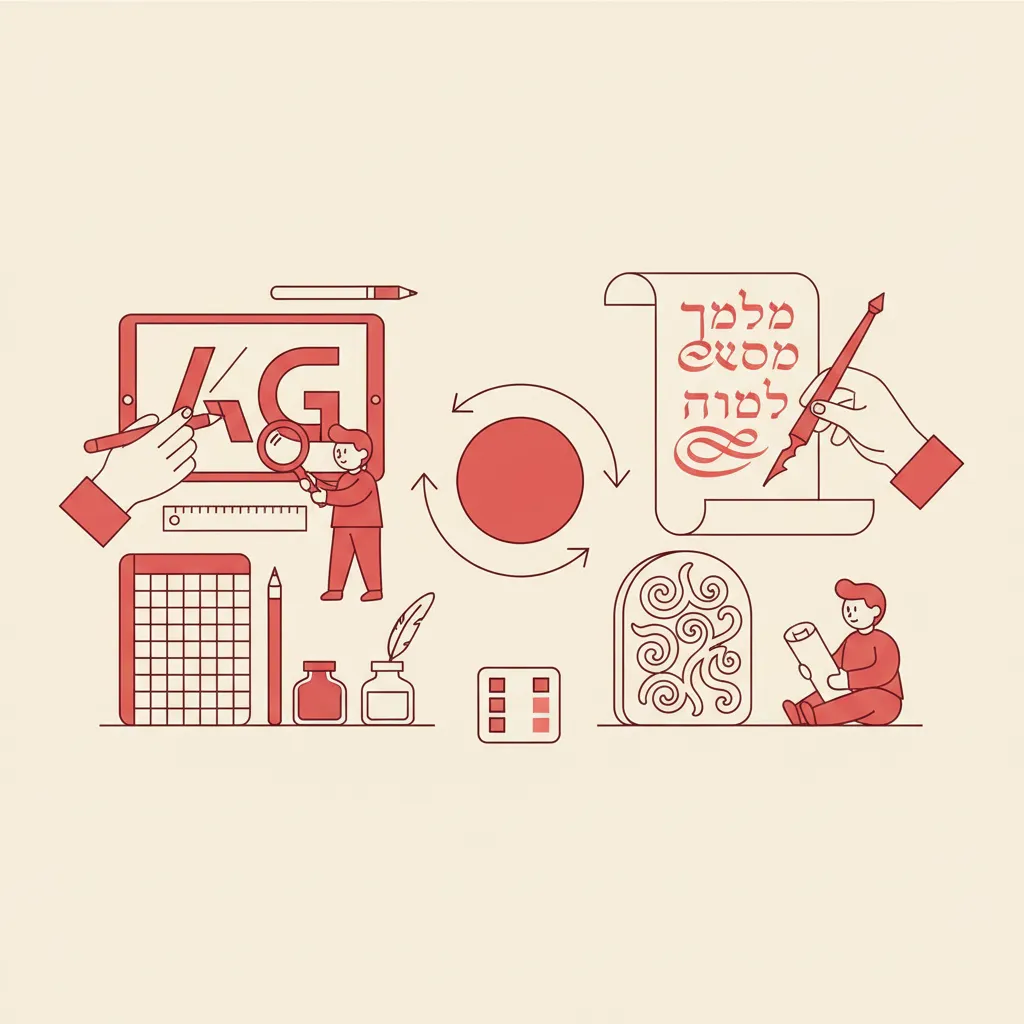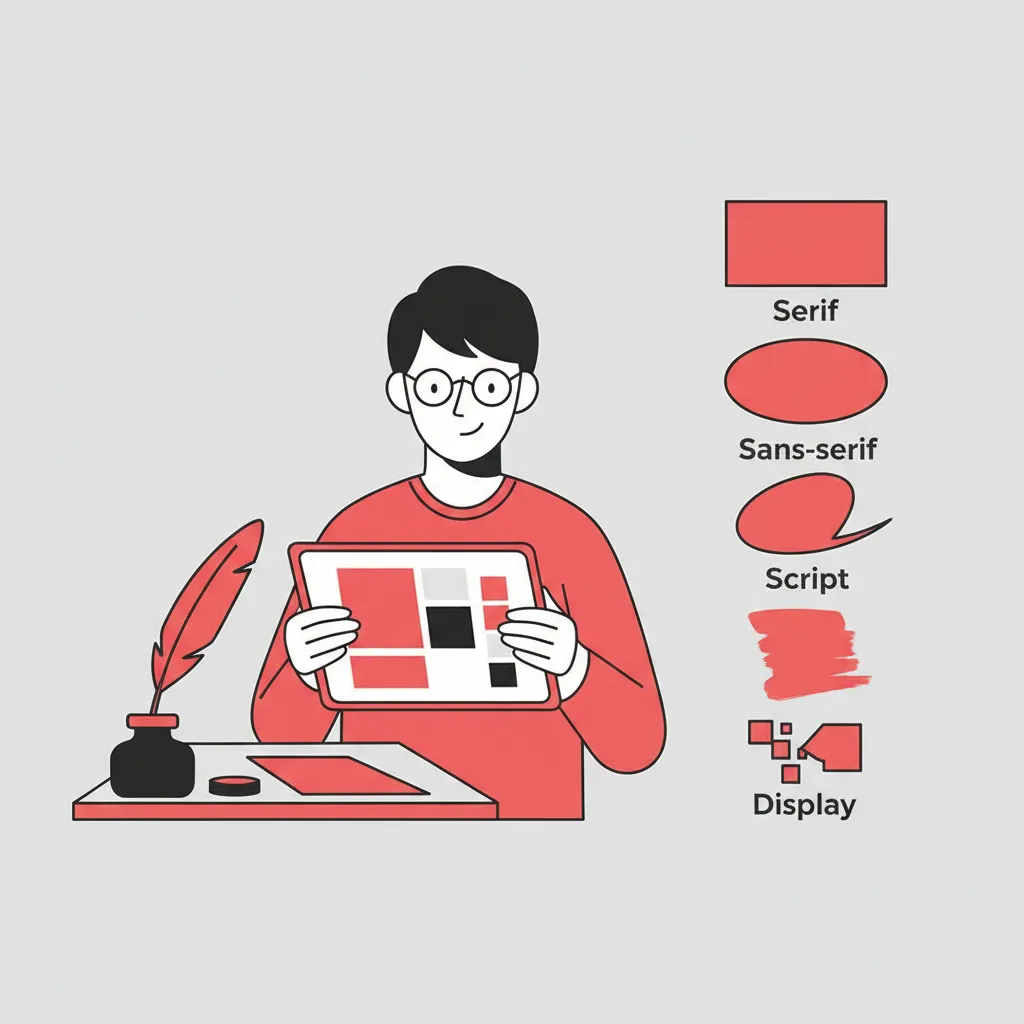
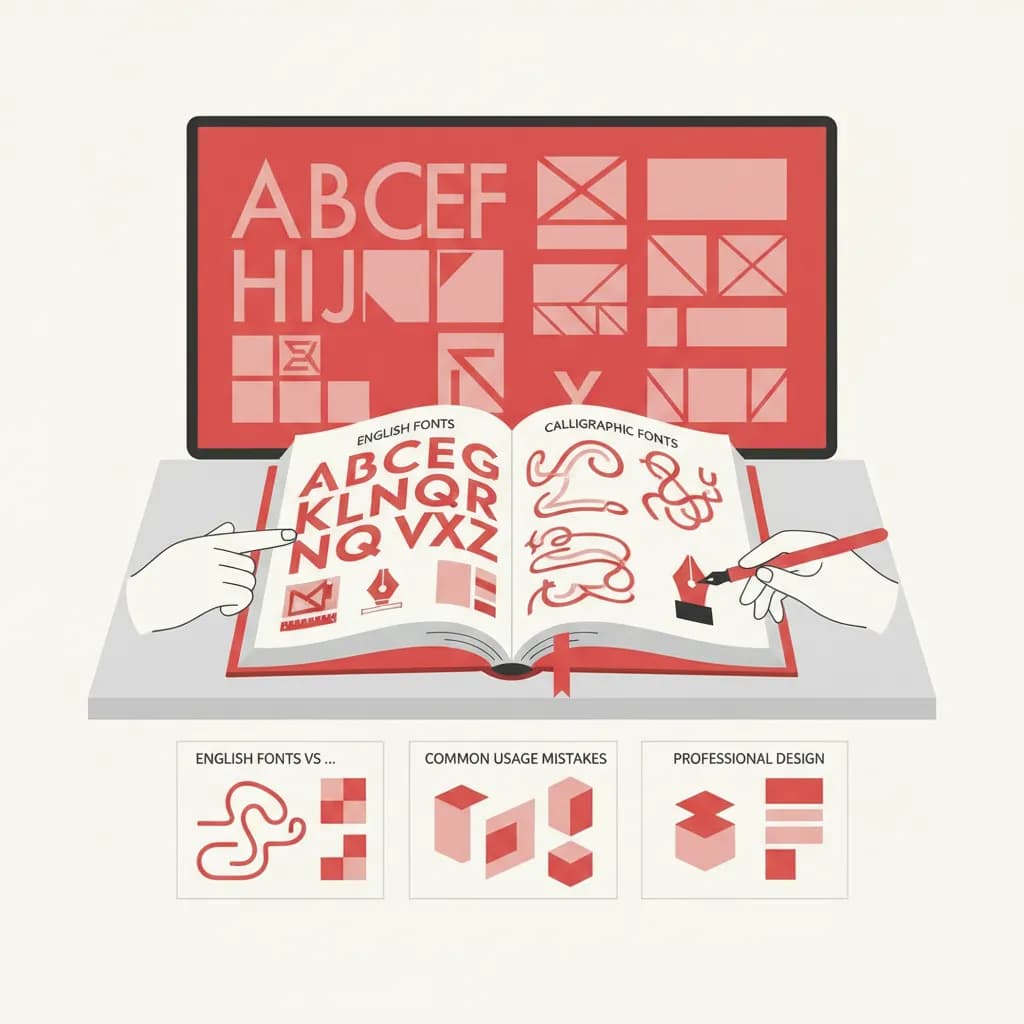
כשמעצב גרפי או בעל עסק מחפש פונטים באנגלית לפרויקט חדש, הוא נתקל מיד בשאלה שמבלבלת רבים: מה ההבדל בין כל הסגנונות הזמינים, ואיזה מהם מתאים לצורך הספציפי שלו? פונטים באנגלית הם עולם עשיר ומגוון, שבו כל סגנון נושא משמעות ויזואלית שונה לחלוטין. הבנת ההבדלים הללו היא המפתח לעיצוב מוצלח – בין אם מדובר בלוגו, הזמנה לאירוע, אתר אינטרנט או חומרי שיווק.
⚡ נקודות מפתח:פונטים באנגלית הם גופנים המעוצבים עבור האלפבית הלטיני, ופועלים על פי עקרונות טיפוגרפיים שונים מהותית מאלה של הכתב העברי. ההבדל הבסיסי ביותר הוא כיוון הכתיבה: אנגלית נכתבת משמאל לימין, בעוד עברית נכתבת מימין לשמאל. הבדל זה משפיע על מבנה האות, על הריווח בין האותיות ועל האיזון הוויזואלי של שורת הטקסט.
ההבדל השני הוא מבנה האות עצמה. בפונטים באנגלית קיים אבחנה בין אותיות גדולות (Uppercase) לקטנות (Lowercase), מה שיוצר מגוון עיצובי עשיר. בעברית אין אבחנה כזו, ולכן מעצבים שעובדים בשתי השפות נדרשים להתאים את הגישה שלהם לכל שפה בנפרד. לקריאה נוספת על עיצוב דו-לשוני, ראו מדריך פונטים בעברית.
ההבדל השלישי נוגע לגודל הניכר של ספריית הפונטים האנגלית. כיום, פלטפורמות כמו Google Fonts מציעות אלפי פונטים באנגלית בחינם, לעומת מאות בודדות של גופנים עבריים איכותיים. הפער הזה משפיע על תהליך הבחירה – כשיש יותר אפשרויות, קל יותר לאבד את הכיוון ולבחור גופן שאינו מתאים לפרויקט.
פונטים באנגלית מתחלקים לארבע משפחות עיקריות, כל אחת עם אופי ויזואלי ייחודי ושימושים מוגדרים. הכרת ההבדלים ביניהן היא הבסיס לכל החלטת עיצוב טיפוגרפי.
פונטי Serif הם גופנים המאופיינים בקצוות קטנים ("כובעונים") בקצות קווי האות. Times New Roman ו-Georgia הם הדוגמאות המוכרות ביותר. פונטים מסוג זה משדרים רשמיות, אמינות ומסורת, ולכן הם נפוצים בעיתונים, בספרים ובמסמכים אקדמיים. הם מתאימים במיוחד לטקסט ארוך בהדפסה, שכן ה"כובעונים" מנחים את העין לאורך השורה.
פונטי Sans-Serif (ללא סריף) הם גופנים עם קווים נקיים וללא קצוות נוספים. Helvetica, Arial ו-Futura הם הנציגים הבולטים. סגנון זה משדר מודרניות, פשטות ונגישות, ולכן הוא הבחירה הנפוצה ביותר לממשקי משתמש דיגיטליים, אתרי אינטרנט ואפליקציות. על מסכים, פונטים ללא סריף קריאים יותר בגדלים קטנים. לעצות נוספות על בחירת פונטים לאתרים, ראו פונטים אופטימליים לווב.
פונטי Script מחקים כתב יד קליגרפי ומשדרים חום, אישיות ואלגנטיות. הם מגיעים בשני סגנונות עיקריים: Formal Script (קליגרפיה רשמית עם קישורים בין האותיות) ו-Casual Script (כתב יד ספונטני ומשוחרר). פונטים אלה מתאימים להזמנות לאירועים, לוגואים בוטיק ועיצוב אריזות יוקרתיות. חשוב לזכור שקריאות שלהם מוגבלת בטקסט ארוך.
פונטי Display עוצבו במיוחד לשימוש בכותרות גדולות ולא לטקסט רץ. הם כוללים סגנונות דקורטיביים, גותיים, רטרו ועוד. מטרתם היא ליצור רושם ויזואלי חזק ולהעביר אישיות מוגדרת. לדוגמה, פונט Display בסגנון וינטאג' יתאים למסעדה שרוצה להדגיש שורשים ומסורת, בעוד שפונט Display גיאומטרי יתאים לסטארטאפ טכנולוגי.
בחירת פונטים באנגלית היא תהליך שמתחיל בהגדרת המטרה – לא בגלישה בספריית גופנים. לפני שפותחים את Google Fonts או Adobe Fonts, כדאי לענות על ארבע שאלות מפתח:
עקרון ה-Font Pairing – שילוב שני פונטים משלימים – הוא אחד הכלים החזקים ביותר בידי המעצב. השיטה הנפוצה ביותר היא לשלב פונט Serif בכותרות עם Sans-Serif בגוף הטקסט, או להיפך. לדוגמה, שימוש ב-Playfair Display לכותרות ו-Source Sans Pro לגוף יוצר ניגוד ויזואלי מרענן שמנחה את העין. לעצות על עיצוב מילים בצורה שמעבירה מסר, ראו עיצוב מילים שמעביר את המסר.
כשעובדים על פרויקטים דו-לשוניים – אנגלית ועברית יחד – חשוב לשים לב לגובה ה-x (x-height) של הפונטים. פונטים באנגלית עם x-height גבוה נראים גדולים יותר ביחס לגובה שלהם, ולכן כדאי לבחור גופן עברי עם פרופורציות דומות. לדוגמה, פונט אספרסו הוא פונט דו-לשוני עם תגיות "סנס סריף" שמתאים לשימוש בסביבה דיגיטלית לצד גופנים אנגליים מודרניים.
מעצבים רבים – מתחילים ומנוסים כאחד – נוטים לחזור על כמה טעויות ספציפיות בבחירת פונטים באנגלית. הכרת הטעויות הללו יכולה לחסוך שעות עבודה ולמנוע תוצאות מאכזבות.
טעות 1: שימוש ביותר מדי פונטים. כלל אצבע מקצועי הוא לא לשלב יותר משלושה פונטים שונים בעיצוב אחד. כשמשתמשים בארבעה, חמישה או יותר פונטים באנגלית באותו עיצוב, התוצאה נראית כאוטית וחסרת כיוון. שני פונטים משלימים מספיקים ברוב המקרים.
טעות 2: בחירת פונט Script לטקסט ארוך. פונטים בסגנון כתב יד אלגנטיים מאוד בכותרות קצרות, אך הם גורמים לעייפות ויזואלית מהירה בטקסט ארוך. אם אתם מחפשים אישיות ייחודית לגוף הטקסט, עדיף לבחור Sans-Serif עם אישיות מוגדרת.
טעות 3: התעלמות מרישיון השימוש. לא כל פונטים באנגלית זמינים לשימוש מסחרי חופשי. פונטים מ-Google Fonts ניתנים בדרך כלל לשימוש מסחרי, אך חשוב לבדוק את תנאי הרישיון של כל פונט בנפרד, במיוחד בפרויקטים מסחריים. אתר Adobe Fonts מציע פונטים פרימיום עם רישיונות מסחריים ברורים.
טעות 4: אי-בדיקת הפונט במדיום הסופי. פונט שנראה מצוין על מסך המחשב עשוי להיראות שונה לחלוטין בהדפסה, על מסך נייד, או בגדלים שונים. תמיד בדקו את הפונטים באנגלית שבחרתם בסביבה הסופית לפני אישור עיצוב.
⚡ צ'קליסט לבחירת פונטים באנגלית:הבחירה בין סוגי פונטים באנגלית תמיד תלויה בצרכים הספציפיים של הפרויקט ובקהל היעד. אין פונט "טוב" או "רע" באופן אבסולוטי – יש פונט מתאים לפרויקט מסוים ופונט שאינו מתאים לו. הנה מדריך מהיר לפי סוג הפרויקט:
עקרון מנחה נוסף: כשעובדים עם פונטים באנגלית בסביבה דיגיטלית, כדאי לבדוק אם הגופן זמין כ-Web Font. פונטים שאינם מותקנים על מחשב הגולש יוחלפו בגופן ברירת מחדל – מה שעלול לפגוע במראה העיצוב. Google Fonts ו-Adobe Fonts מציעים Web Fonts מוכנים לשימוש עם קוד טעינה פשוט.
הנקודות המרכזיות שחשוב לזכור: בחרו פונטים באנגלית בהתאם למדיום ולמטרה, לא לפי העדפה אסתטית בלבד. הגבילו את מספר הפונטים לשניים-שלושה לכל פרויקט. תמיד בדקו רישיונות שימוש לפני שימוש מסחרי. ובפרויקטים דו-לשוניים – השקיעו זמן בהתאמה הוויזואלית בין הפונט האנגלי לגופן העברי.
פונטים באנגלית ועברית עובדים לפי עקרונות שונים, אך כשבוחרים אותם בתשומת לב ובהבנה, הם יכולים לשלב ולהשלים זה את זה בצורה יוצאת דופן. המדריך לבחירת פונט באנגלית שלנו יכול לעזור לכם להעמיק עוד יותר בנושא ולמצוא את הגופן המושלם לפרויקט הבא שלכם.